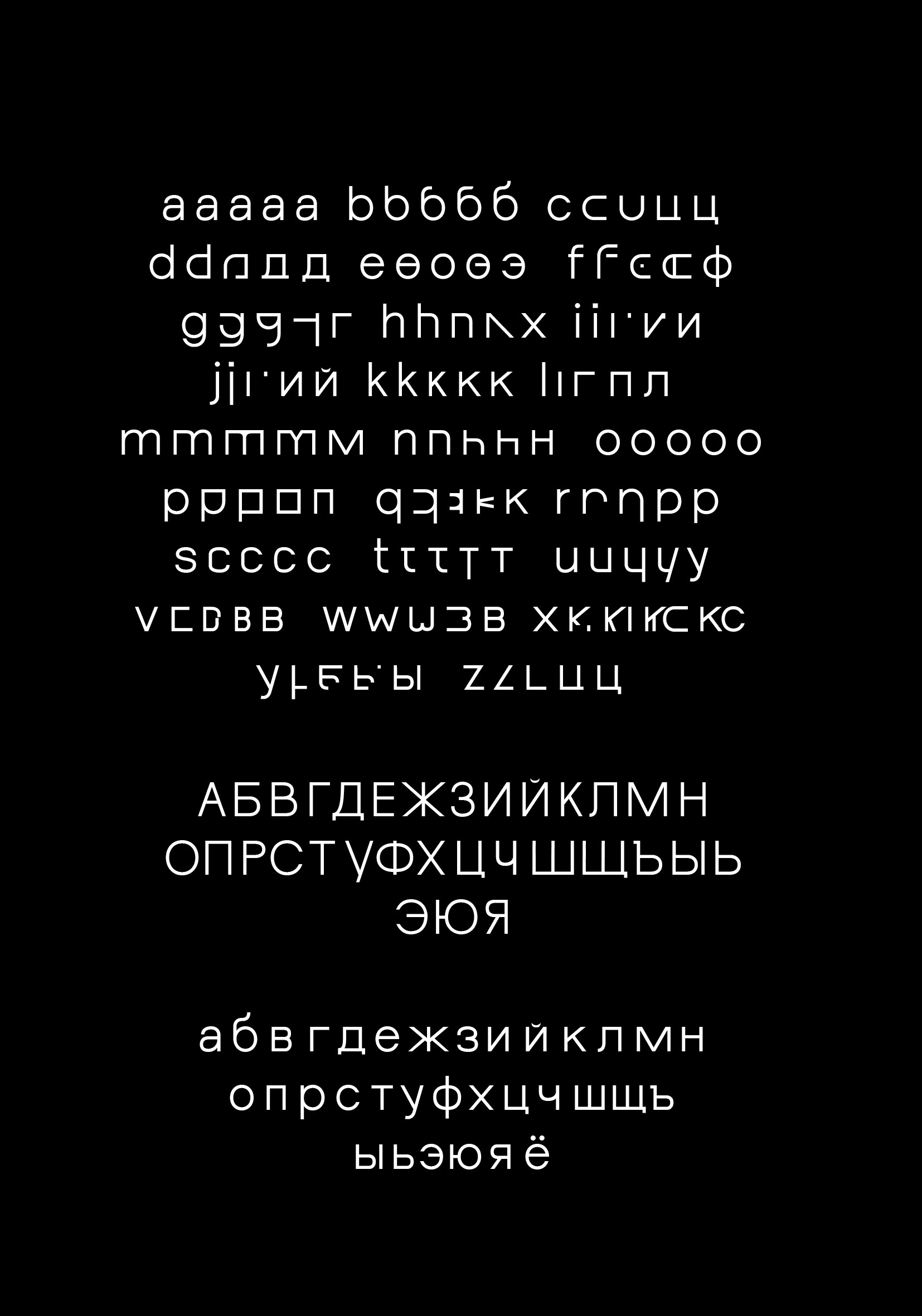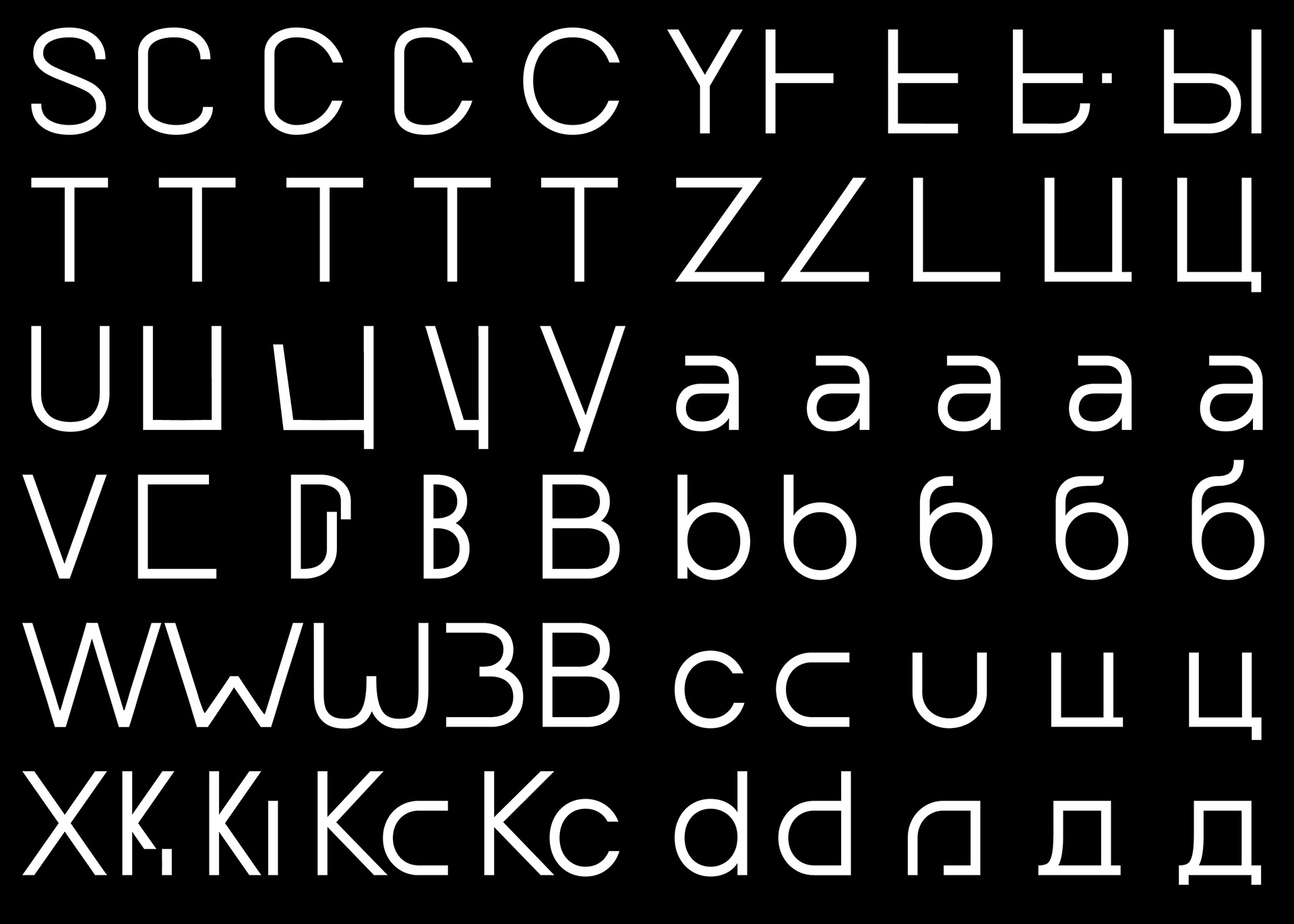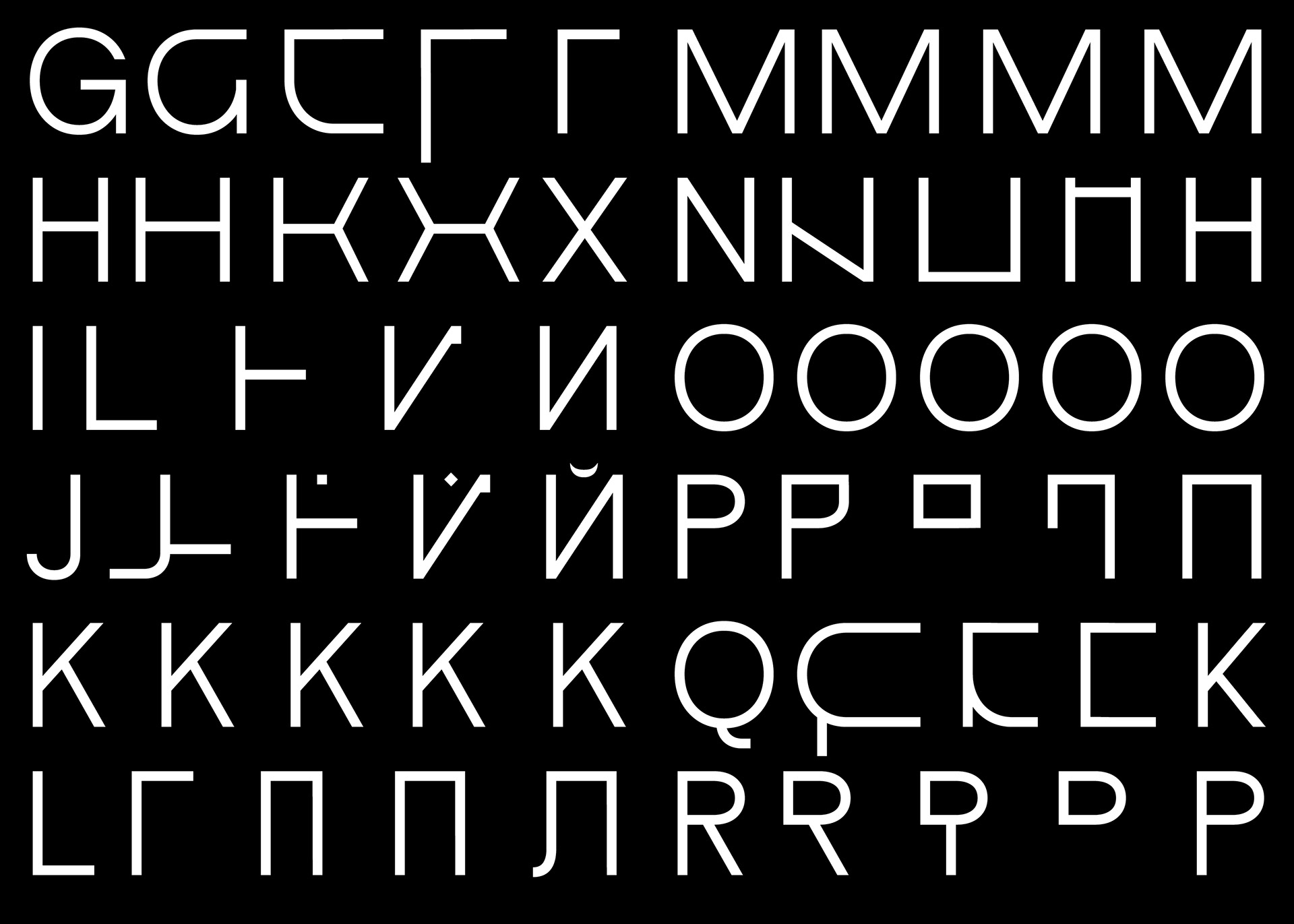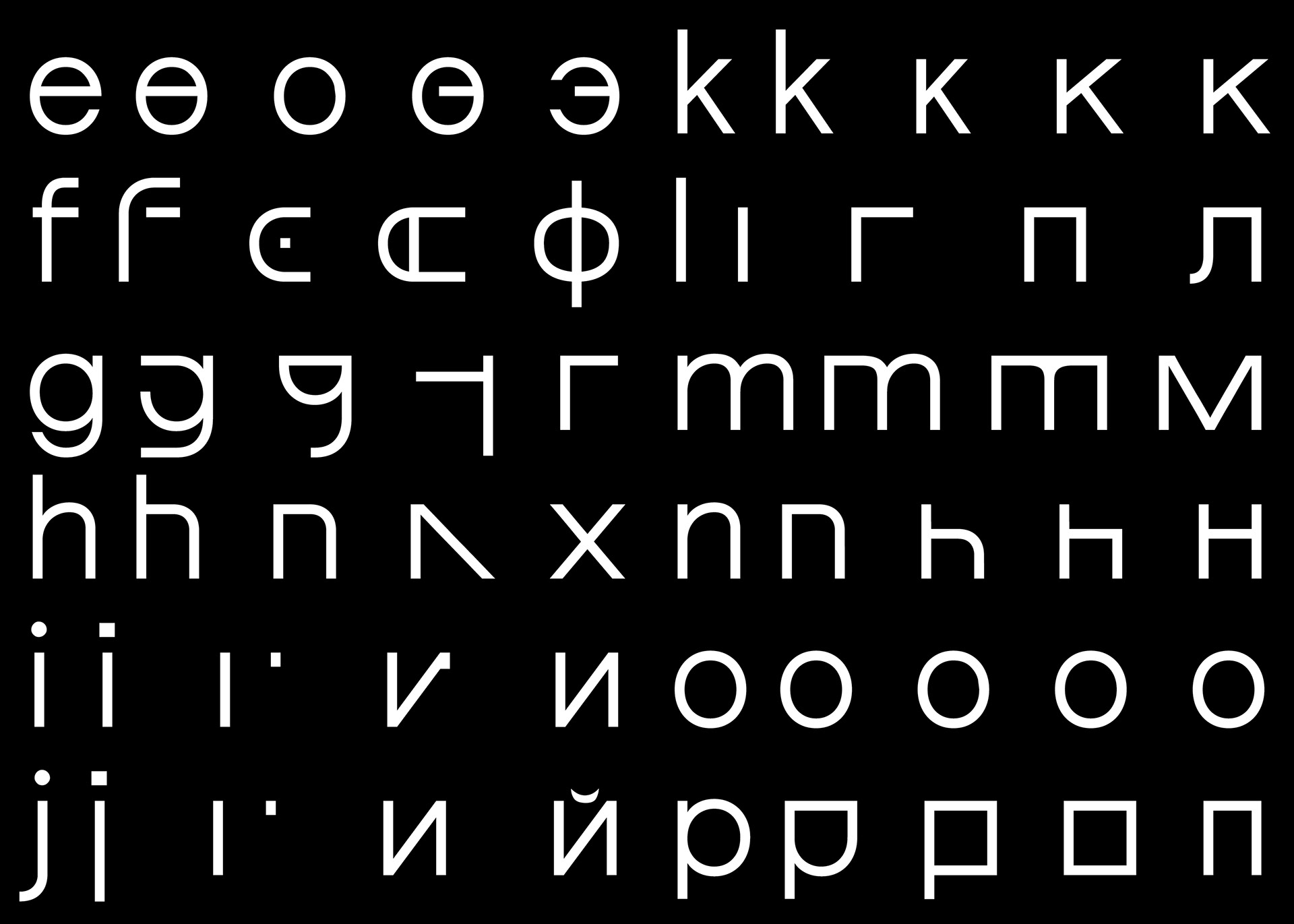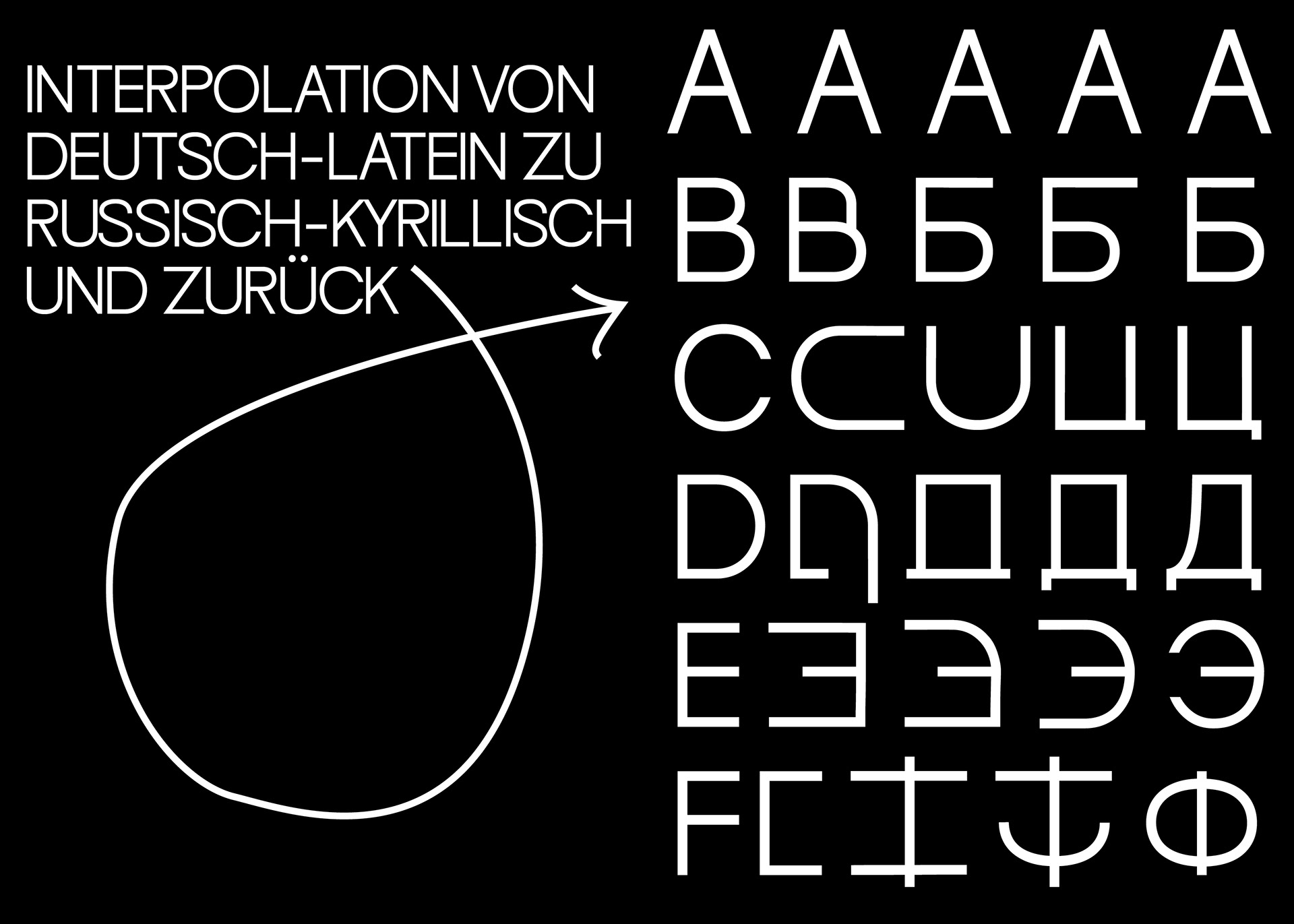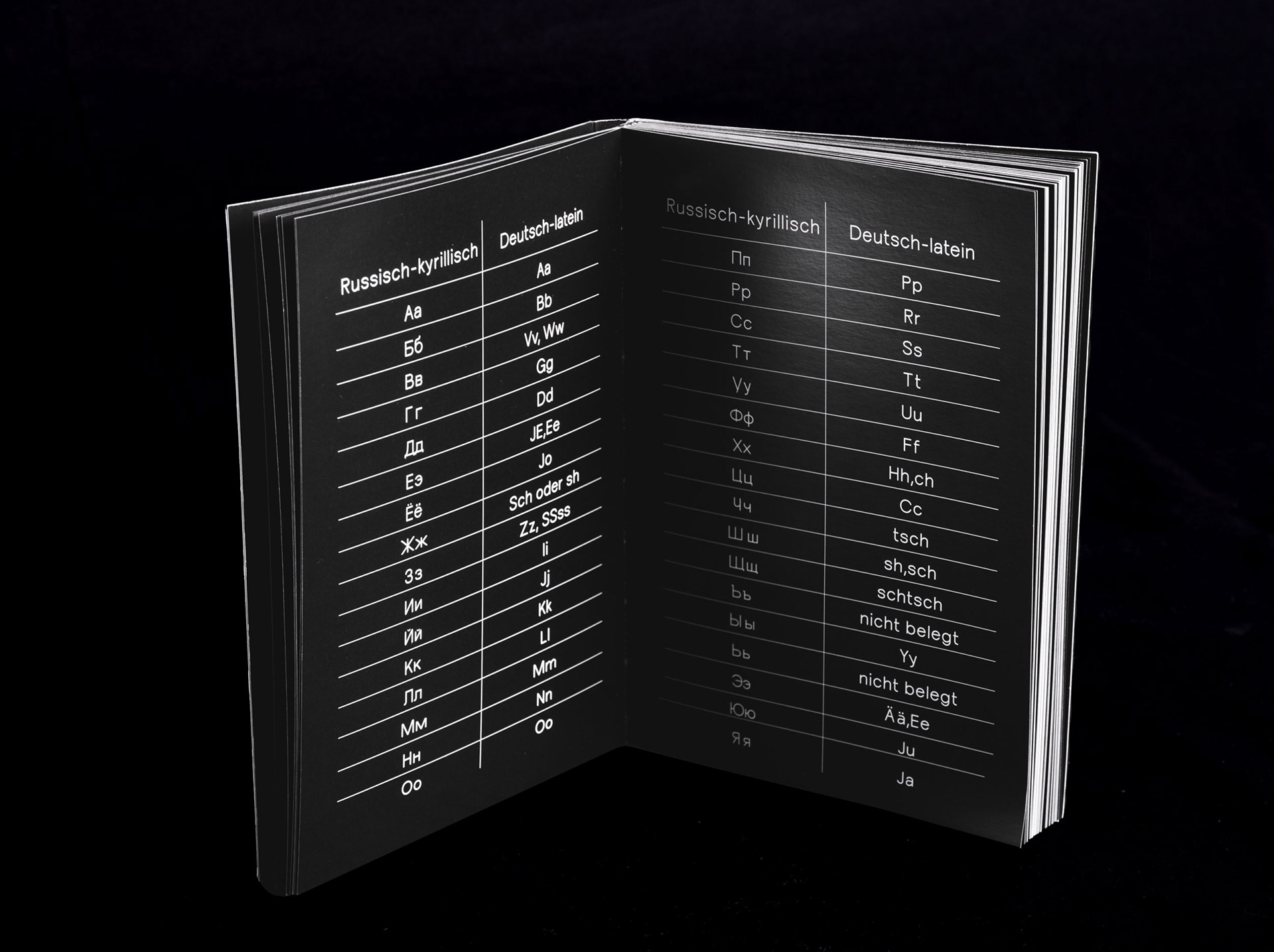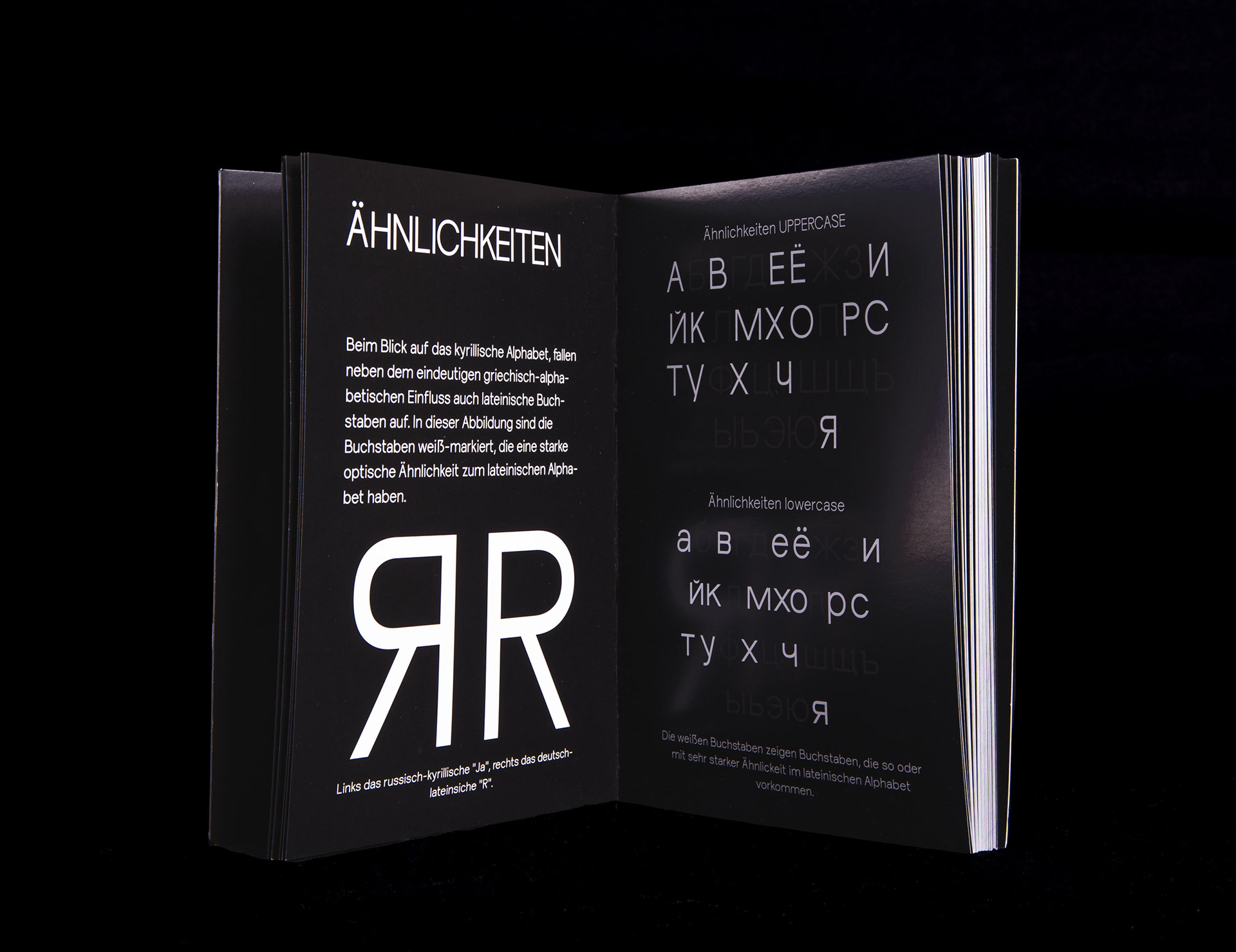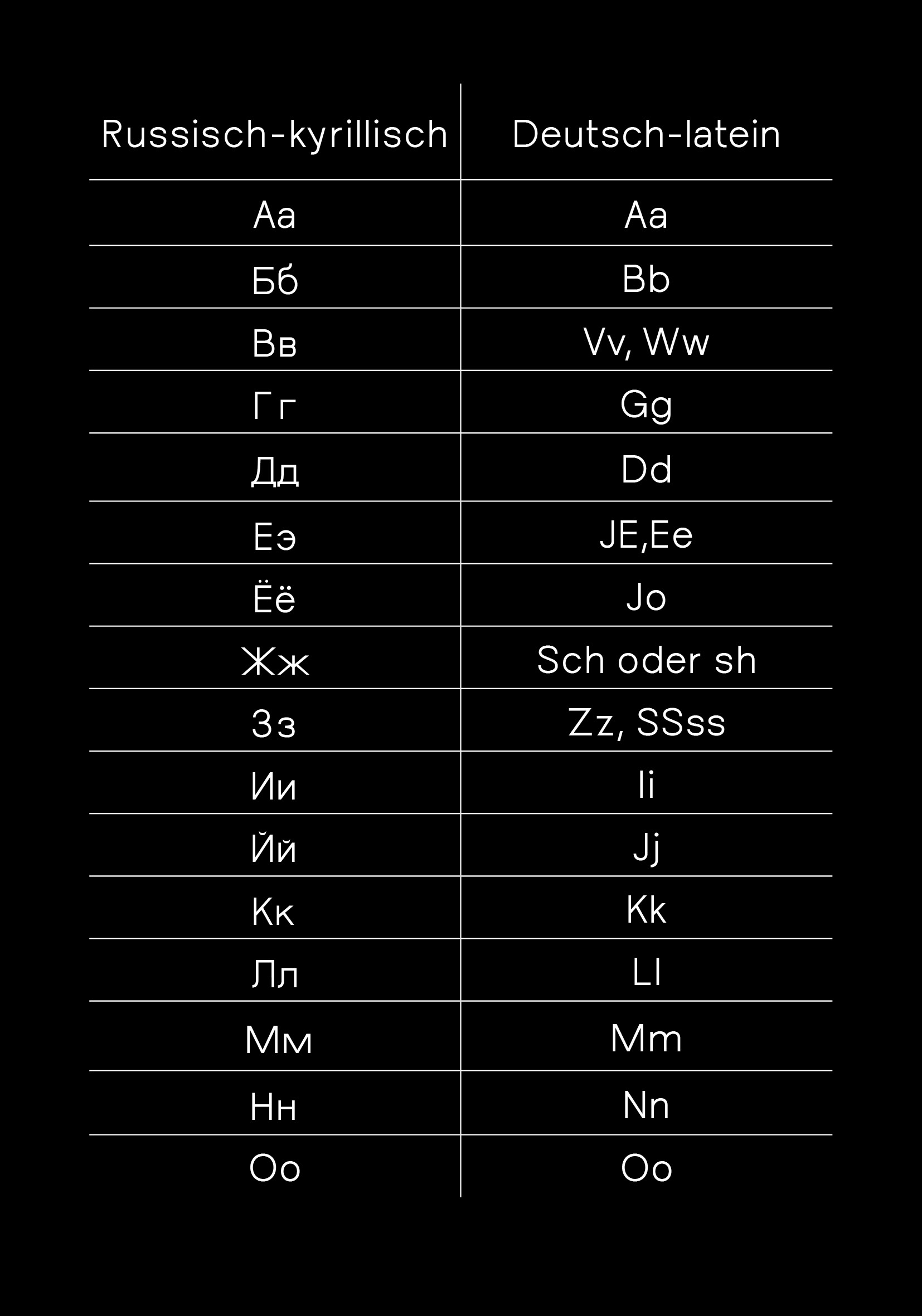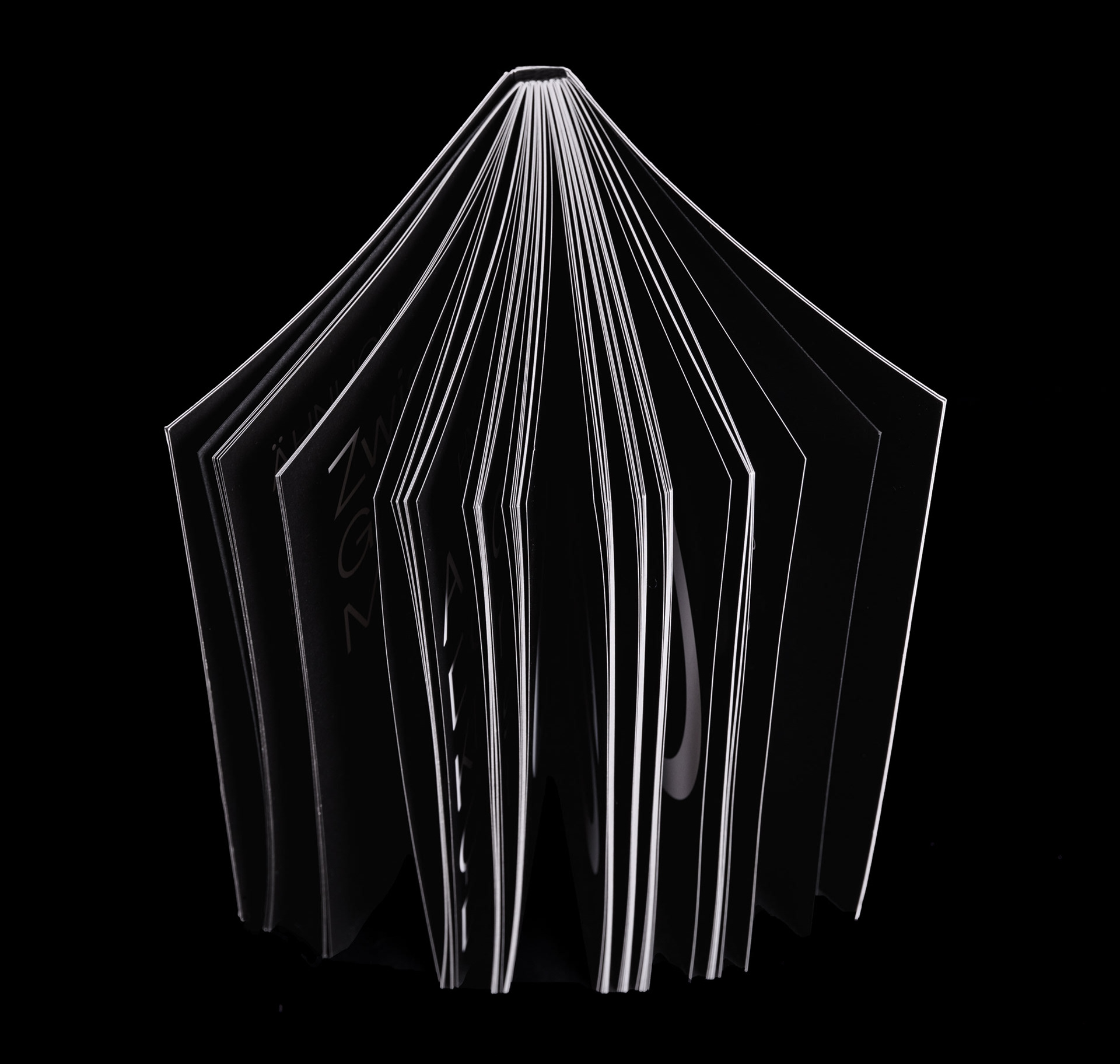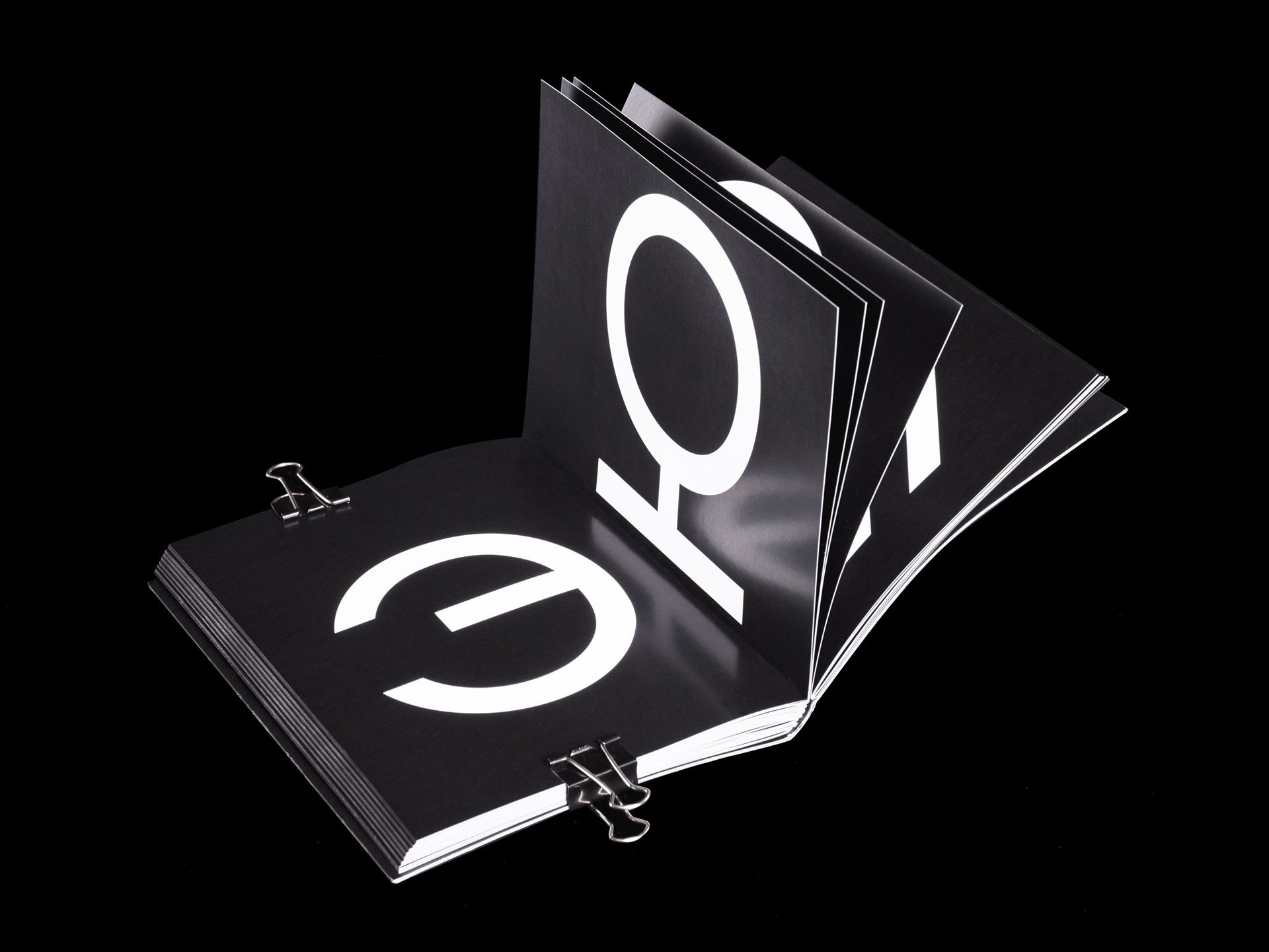
Kaizar – ein variabler deutschrussischer Font
Variable Fonts haben in den letzten Jahren immer mehr Aufmerksamkeit in der Typografie- und der Designerszene bekommen. Die Grenzen bei einer variablen Schrift scheinen aber noch nicht erschöpft zu sein. Was genau ist also noch mit dieser „jungen“ Technologie möglich? Ist es möglich einen variablen Font zu designen, der zwischen verschiedenen Schriftsystemen interpolieren kann? Welche Kriterien und Regeln muss man bei so einer speziellen Gestaltung beachten? In meiner Bachelorarbeit „Zwischen Gartenzwergen und Matrjoschkas“ bin ich dieser und weiteren Fragestellung zum Thema Schriftsystem-Interpolation nachgegangen. Dabei herausgekommen ist die deutschrussische variable Font „KAIZAR“.
Als Russlanddeutscher bin ich dauerhaft in Kontakt mit der deutschen und russischen Kultur und somit auch mit den verschiedenen Sprachen und Schriftsystemen. Wenn russisch gesprochen wird, bleibe ich aber bei einer deutschsprachigen Antwort. In bilingualen Haushalten ist das nicht untypisch. Bei Freunden und Verwandten, die dieselbe ethnische Herkunft aufweisen, habe ich dieses Muster immer wieder erkannt. Im Haushalt wird mal die eine, mal die andere Sprache gesprochen. In meinem Fall war es ein Misch-Masch aus beiden Sprachen.
Beispiel:
Wowa, можешь дать мне die Fernbedienung?
Übersetzt: Waldemar, kannst du mir die Fernbedienung geben?
Diese “fusionierte Sprache" hat mich dazu inspiriert eine deutschrussische variable Font zu entwerfen, die auf ihren Achsen zwischen dem deutsch-lateinischen und russisch-kyrillischen Schriftsystem interpoliert und jeden einzelnen Letter in das eine oder das andere Schriftsystem phonetisch korrekt übersetzt. Durch die Interpolation von dem einen in das andere Schriftsystem entstehen Hybride Letter, die die fusionierte Sprache darstellen.
Identifikation
In meiner Recherche zu der ethnischen Identifikation von Russlanddeutschen bin ich auf eine Umfrage der Boris-Nemtsov-Foundation gestoßen, die meine Vermutung unterstütze, dass sich junge russlanddeutsche sich mal mehr der einen oder anderen Identität zugehörig fühlen, oder sich dazwischen befinden. Ganz ähnlich ist die variable Font Kaizar. Sie ist mal deutsch, sie ist mal russisch und sie ist auch mal irgendwas dazwischen.
Ähnlichkeiten
Beim Blick auf das kyrillische Alphabet, fallen neben dem eindeutigen griechisch-alphabetischen Einfluss auch lateinische Buchstaben auf. In dieser Abbildung sind die Buchstaben weiß-markiert, die starke optische Ähnlichkeiten zum lateinischen Alphabet haben.
Übersetzung
Der wichtigste konzeptionelle Bestandteil des "russlanddeutschen" variablen Fonts ist die korrekte Übersetzung jedes einzelnen Buchstabens vom Russischen ins Deutsche und umgekehrt. Bei der Übersetzung habe ich mich an die Regeln der Transliterations- und Transkriptionstabelle des Instituts fürs Übersetzen und Dolmetschen der Universität Heidelberg, wie auch an die Transkriptionstabelle des Dudens gehalten.
Besonders interessant und herausfordernd, war es die deutschen Buchstabenkombinationen, wie z.B. ch, ei, ie, uh, oh, ck oder sch zu übersetzen. Dafür mussten komplett neue Ligaturen erstellt werden. Das „e“ in der Buchstabenkombination „ei“ wird z.B. wie ein „a“ ausgesprochen, d.h. in der russischen Übersetzung muss auch ein A anstelle eines E stehen.
Pfade
Die einzelnen Letter bestehen aus ungewöhnlich vielen Konturen, damit auch komplexe Interpolationen, wie z.B. zwischen dem lateinischen F in ein kyrillisches F möglich sind. Hierbei war ich nicht nur in der Funktion eines Schriftgestalters, sondern auch eines Motion-Designers tätig.
Hybride
Durch die Interpolation vom Latein-Master in den Kyrillisch-Master entstehen neue, individuelle Letter.
Alle Letter
Die gesamte Schriftart enthält Upper- und Lowercse des lateinischen, wie auch des kyrillischen Alphabets. Die Strichstärke erreicht die Maße eines klassischen „Regular“ Schriftschnitts. Zudem enthält die Schrift enthält alle Zahlen, wie auch eine Auswahl an Symbolen. Insgesamt beinhaltet die Schrift KAIZAR 309 Glyphen.
Specimen Kaizar
Zu dem variablen Font ist ein Specimen entstanden, der meine Erkenntnisse zu einem deutschrussischen oder auch multikulturellen variablen Font zusammenfasst.